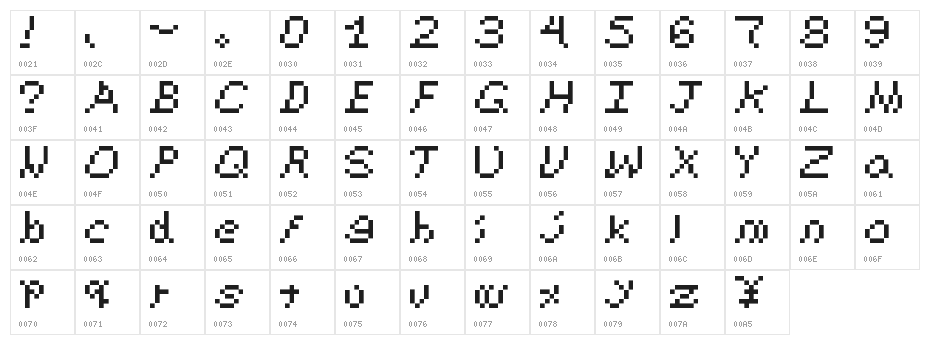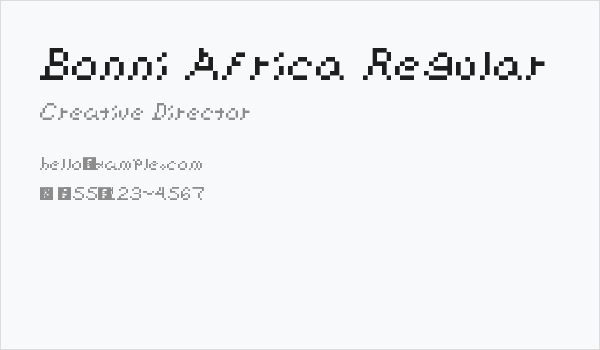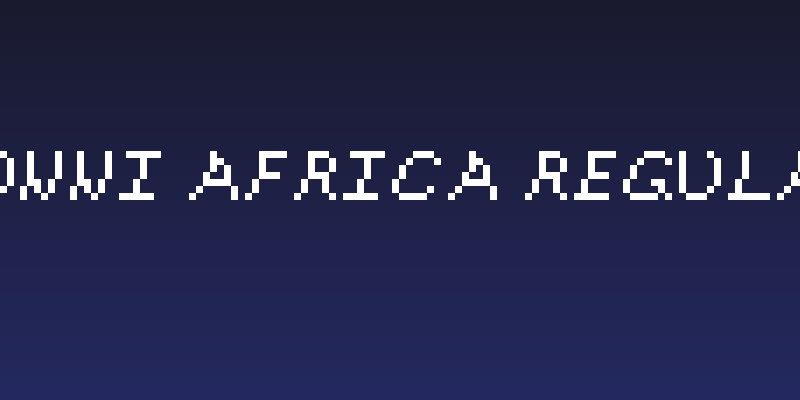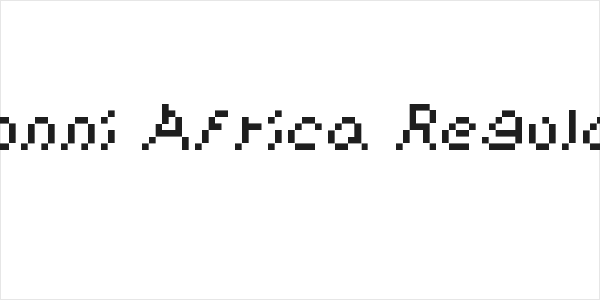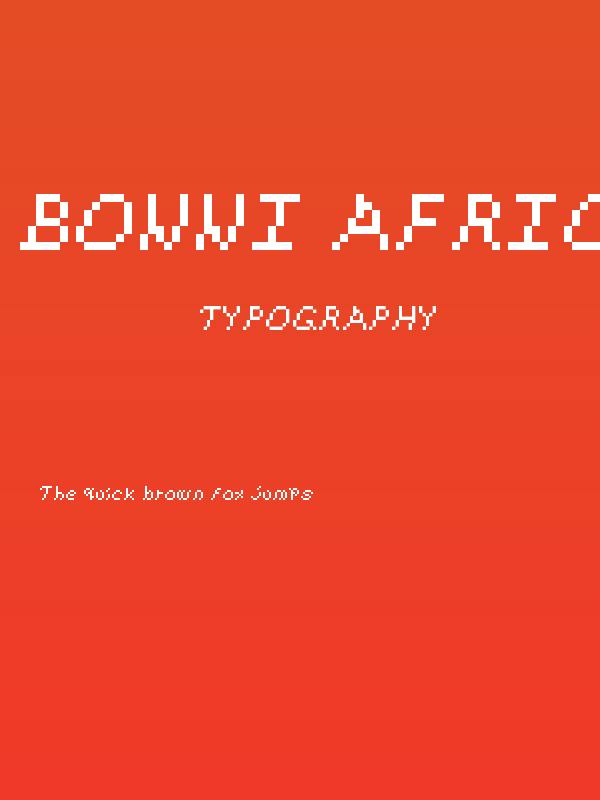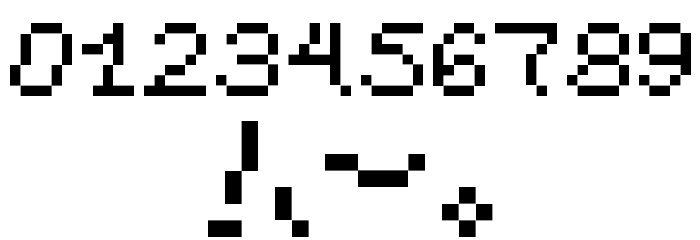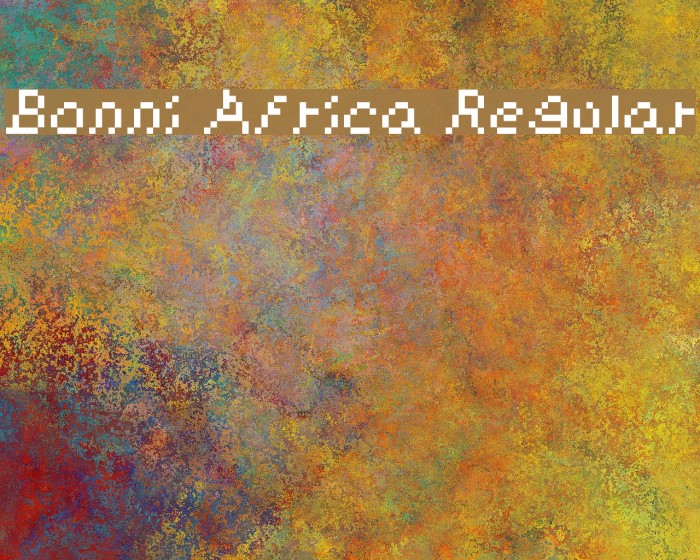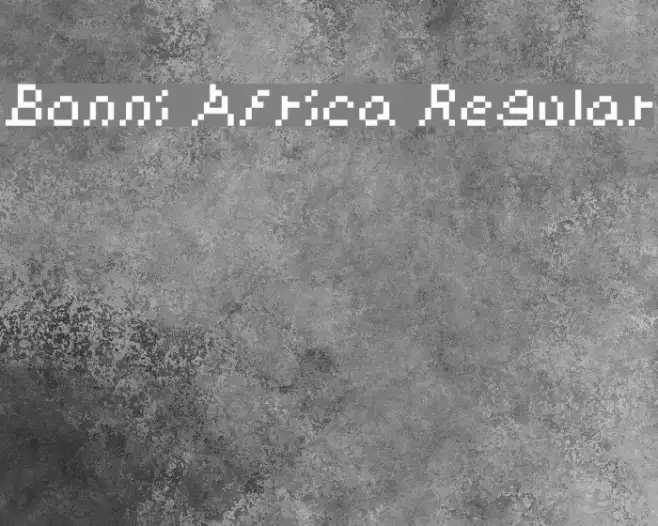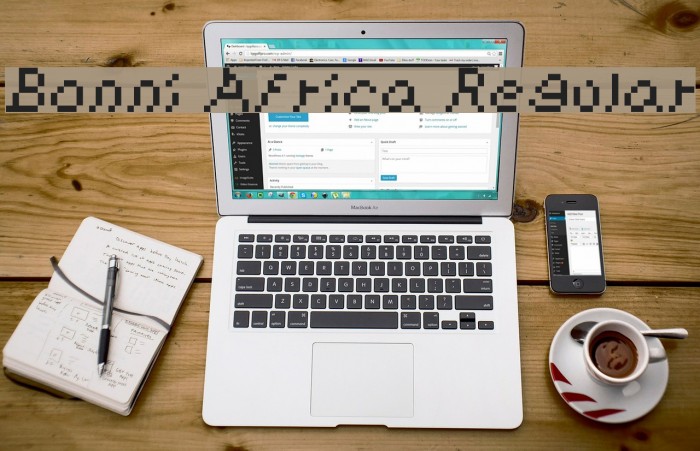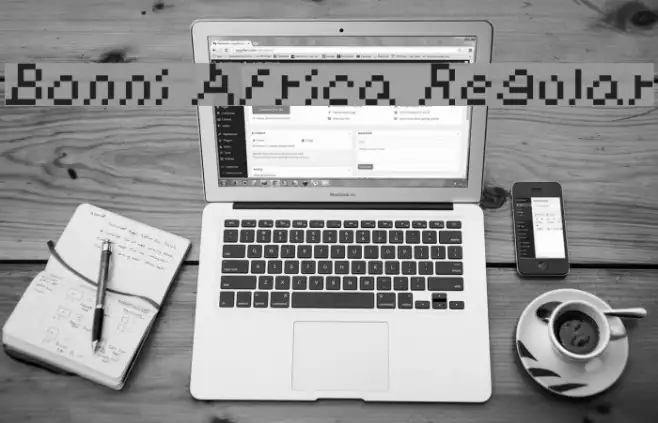
Bonni Africa Regular Font
✎ Pixel
| Schriften Familie | Bonni Africa |
| Kategorien | Pixel |
| Gesamtstil | Retro, Digital |
| Anwendungsfall | Headlines, Logos, Digital Art |
| Vorgeschlagene Projekte | Ideal for video game design, digital art projects, retro-themed posters, and any creative work that requires a nostalgic or tech-inspired look. |